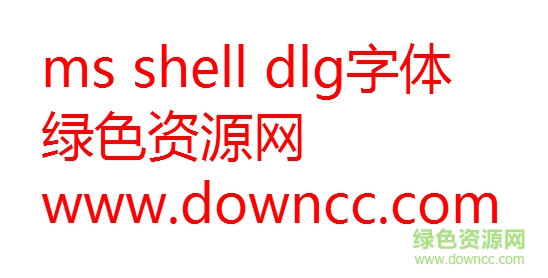
默认的字体是MS Shell Dlg(8),而MS Shell Dlg本身并不是一种字体,只是一种字体映射。以中文Windows XP平台为例,MS Shell Dlg(8)即为宋体(9.5)。映射的字体在注册表中可以指定,好处是可以动态更改其他应用程序的字体--当然前提是使用这个字体映射的vc 对话框字体指定是在.rc资源文件中指定。
MS Shell Dlg 字体的刷新速度要比实际指定的其他字体速度慢,所以在某些情况下会显示不正常,所以在程序中尽可能要少用这样的字体而是指定为具体的字体,如宋体等,使用宋体的刷新速度就比较快,减少了寻找映射的时间。